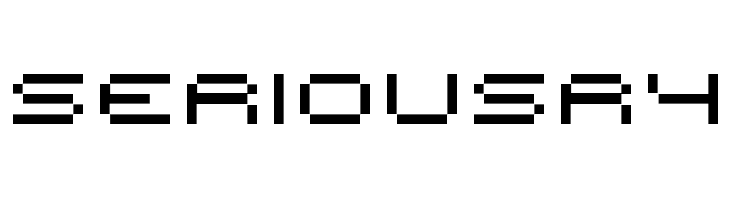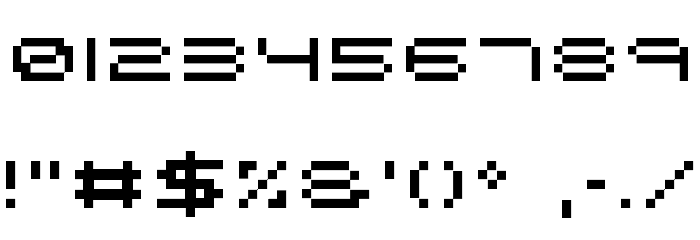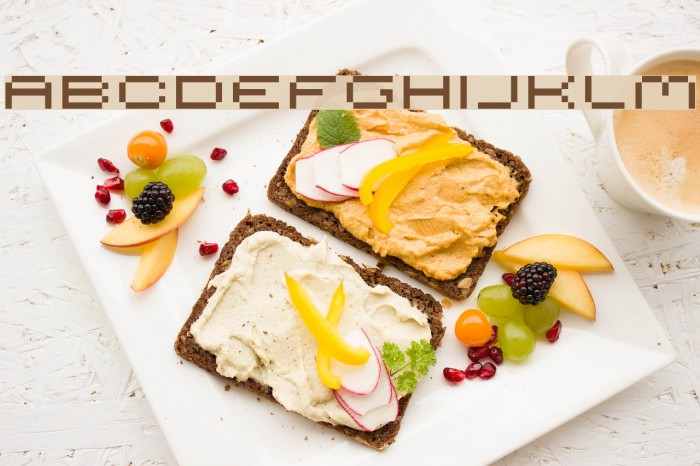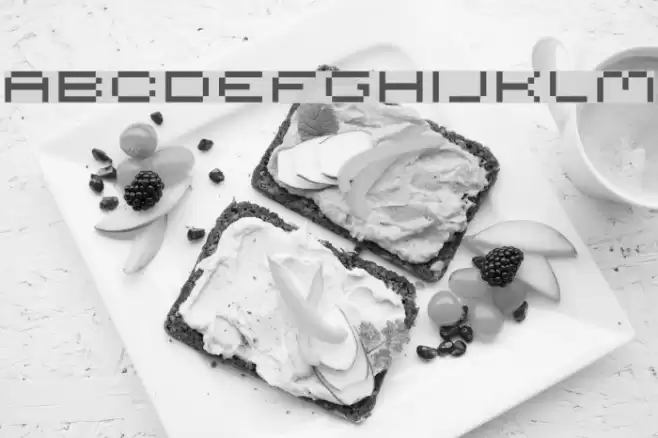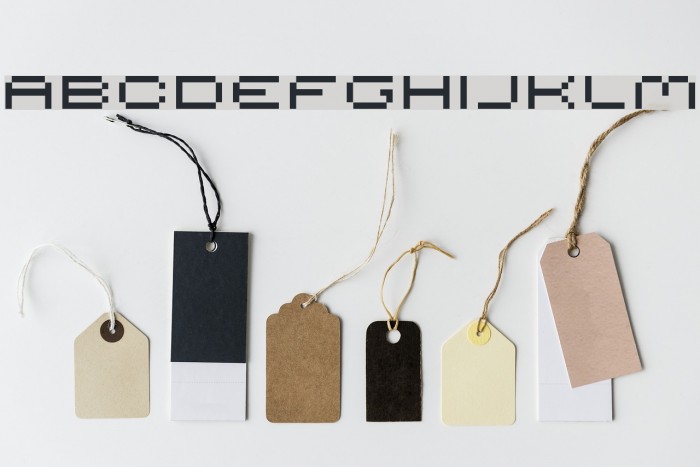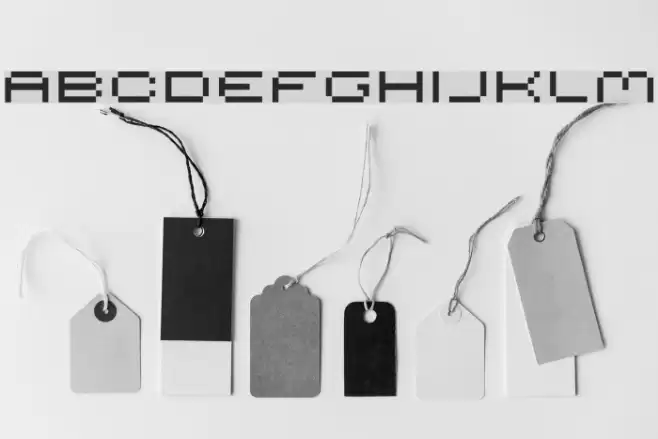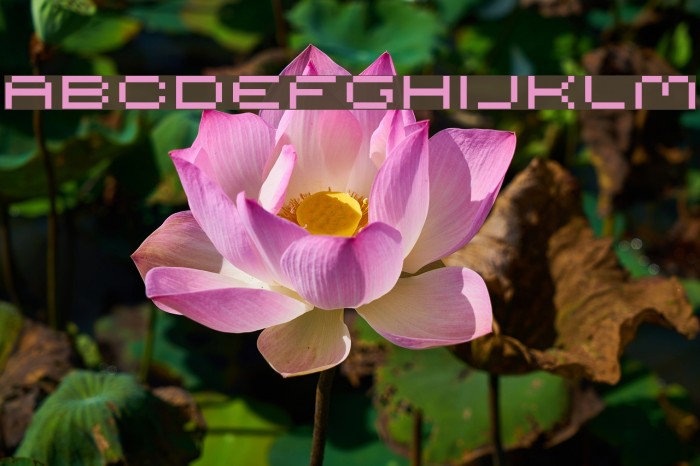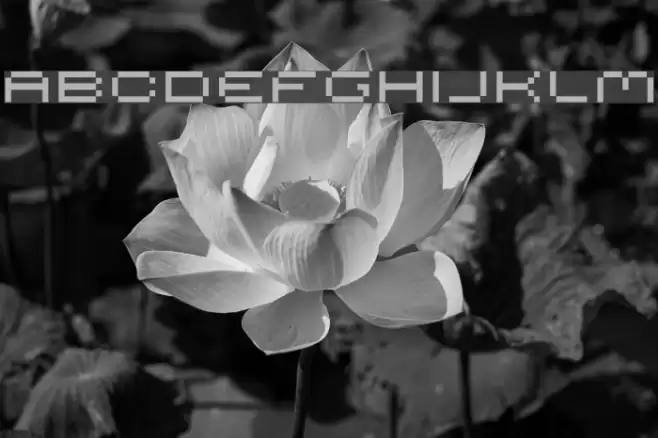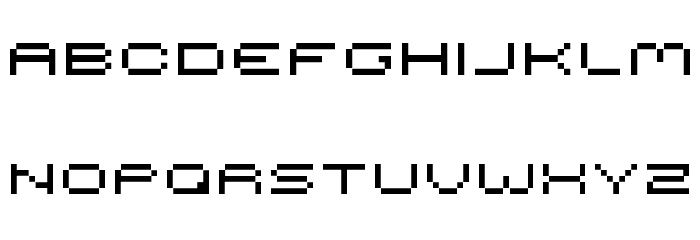
seriousr4 Font
✎ Pixel
| Stile generale | Retro, Digital |
| Progetti proposti | Ideal for projects that require a retro or digital theme, such as video game graphics, tech-themed posters, or digital art. |